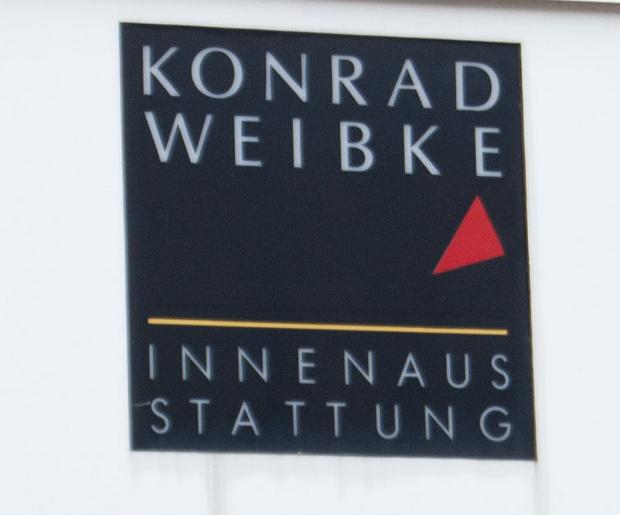
Trennung günstig?
Um nun mein Auge etwas zu schulen habe ich angefangen in meiner Umgebung Schilder auf ihre grafische Umsetzung zu untersuchen.
Dieses Schild scheint mir auf den ersten Blick recht wohlgestaltet zu sein. Viel besser als das Meiste das meine ländliche Gegend sonst so bietet.
Aber bei den zwei unteren Zeilen stößt mir immer wieder die Trennung auf.
Obwohl korrekt, scheint sie mir unglücklich gewählt.
Meine Frage: ist das in diesem Fall der Ausgewogenheit des Schriftzuges unterzuordnen, oder hätte man besser eine andere Lösung finden sollen?
… Obwohl korrekt, scheint sie mir unglücklich gewählt.…
Korrekt ist eine Trennung dann, wenn sie ein Trennzeichen aufweist. Das finde ich auf deinem Beispiel nicht … ;-) "Schaut her wie kreativ ich bin" soll uns das Schild sagen. Ich finde es schlicht schlecht.
Meine Frage: ist das in diesem Fall der Ausgewogenheit des Schriftzuges unterzuordnen, oder hätte man besser eine andere Lösung finden sollen?
Die Trennung ist fürchterlich, ganz allgemein kann man sagen, daß solcherart erzwungene Blöcke nur in sehr seltenen Fällen zu einem annehmbaren oder gar guten Ergebnis führen. Meist ist eine andere Lösung besser.
Die Lesefunktionalität wurde im Beispiel klar der Form untergeordnet, dabei sollte sich doch die Form der Funktion unterordnen. Sooft ich mir das Schild ansehe, bleibe ich an der Trennung hängen, und das ist ja nun nicht Aufgabe eines Schildes.
Das Schild, welches Du uns zeigst, ist ein ganz typisches Gestaltungsbeispiel. Typisch warum? Also: Man kann ja sehen, dass derjenige, der das Schild entworfen hat, sich durchaus Gedanken gemacht hat. Sein gestalterisches Konzept sieht vor, die Textinhalte in einen erzwungenen Blocksatz zu setzen, um damit die geometrische Form des Kastens zu betonen. An sich kein schlechter Gedanke, aber gerade bei solch scheinbar einfachen Aufgaben steckt der Teufel im Detail. In diesem Fall bedeutet das: Der optische Ausgleich der Versalien wurde nicht sorgfältig ausgeführt, beziehungsweise er wurde der Blocksatzidee geopfert, sodass der Schriftrhythmus nicht harmonisch läuft. Die Abstände im Wort WEIBKE sind zu groß im Vergleich zum KONRAD, dafür wurde – Du hast es angemerkt – unten eine unschöne Trennung in Kauf genommen, die – noch schlimmer! – unter Weglassung des notwendigen Trennstriches noch problematischer wird, weil sich der Leser augenblicklich fragt, was ein »Innenaus« wohl ist. Wenn Du Dir im Wort WEIBKE die Abstände zwischen W und E einerseits und K und E andererseits anschaust, dann siehst Du, was ich mit dem unharmonischen Buchstabenrhythmus meine.
Ich verstehe aber auch was Du meinst, wenn Du das Schild für eines der besser gestalteten Schilder in Deiner ländlichen Umgebung hältst. Durch relativ preiswert verfügbare Grafikprogramme kann heute jeder Copyshopbesitzer auch Schilder in sein Angebot aufnehmen, die er dann sicherlich mit Feuereifer aber leider auch bar jeder gestalterischen Ausbildung zusammenbastelt. Mit vermutlich augenschädlichen Ergebnissen.